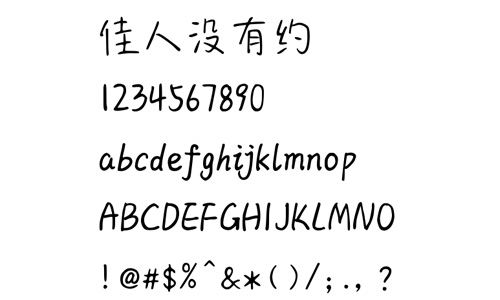
佳人沒有約字體是思雨字庫中的一款硬筆手寫字體,“才子配佳人,佳人心無念,有約不來,空余嘆。”——佳人沒有約字體。本字體是在國家標準簡體字庫GB2312所包含6763漢字的基礎(chǔ)上,又增加了近200常用字,已經(jīng)覆蓋了大陸99.75%的漢字使用頻率,足以滿足日常需求。歡迎喜歡此字體的朋友前來下載使用。